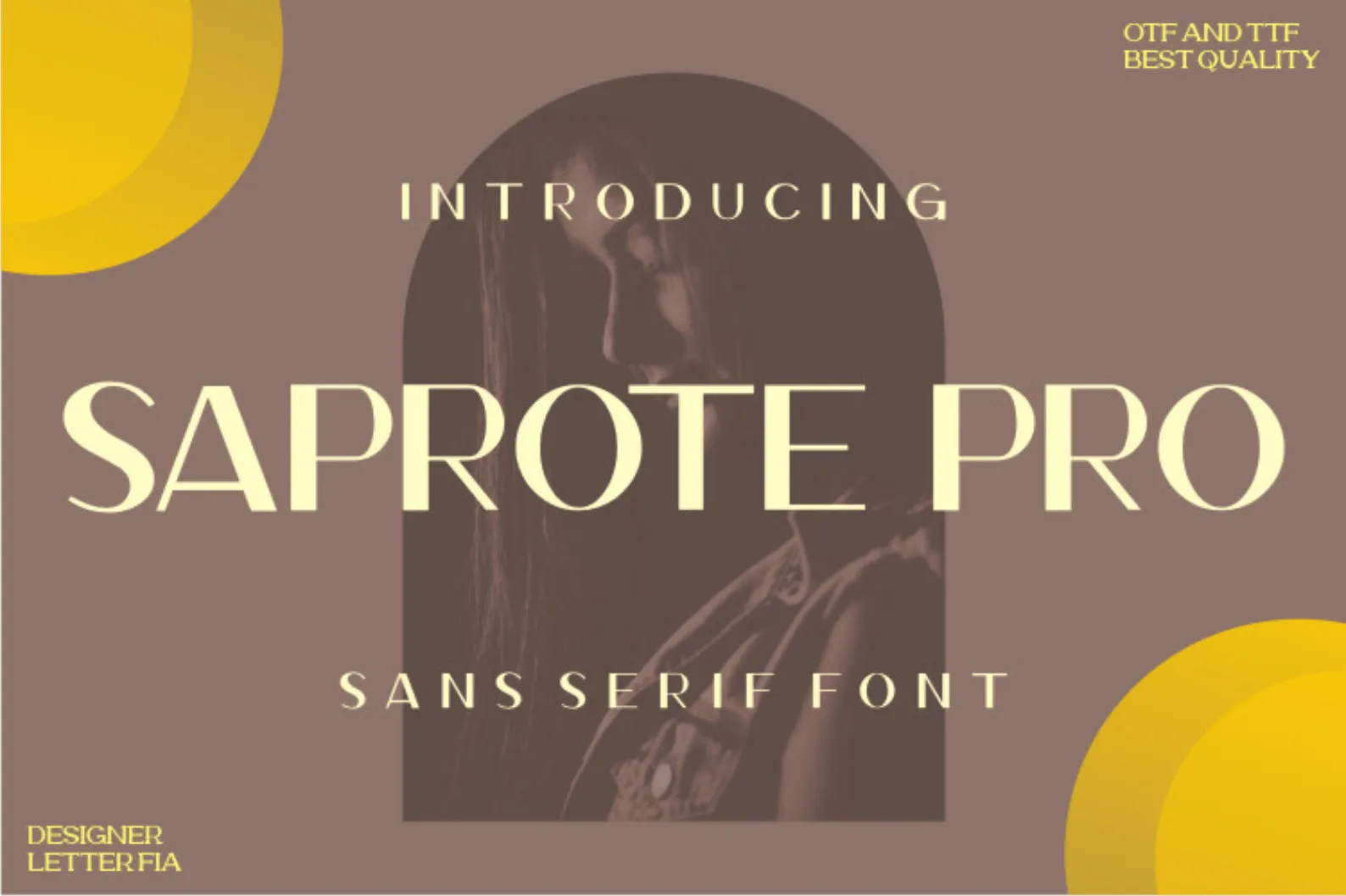
Saprone Font – Download Grátis
Esta é uma fonte sans serif elegante, assertiva e adaptável. Ideal para escrita de designs web, cartões de visita ou praticamente qualquer coisa que precise de uma pegada única. A Saprone Font combina estilo moderno com facilidade de leitura, tornando-a uma escolha perfeita não apenas para designers gráficos, mas também para aqueles buscando um toque diferenciado em seus materiais impressos ou digitais. Seja você um designer web, editor de fotos ou criador de blogs, a Saprone é uma fonte versátil que certamente vai destacar seu trabalho.
Designer: letterfiastudio